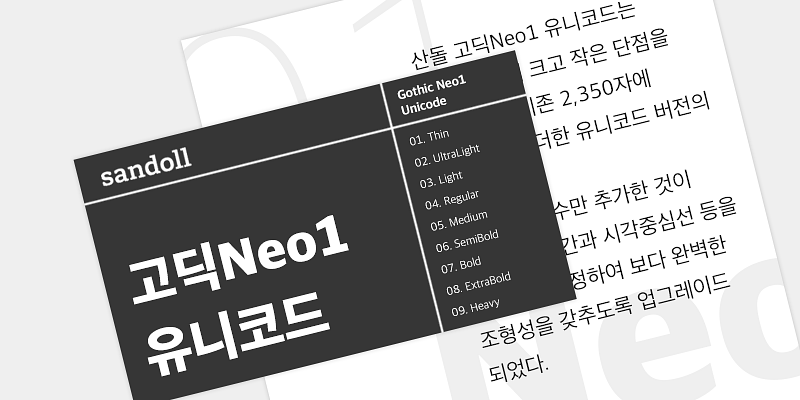
Sandoll GothicNeo1 est une police gothique haut de gamme avec une superfamille de différentes graisses.
Cette police, qui fait partie de la série Sandoll Neo, allie la technologie et la grande expérience de Sandoll dans la création de polices, en modernisant l’élément traditionnel de la Sandoll Gothic.
La police est optimisée pour le confort de l’utilisateur, et les lettres carrées de base ainsi que les espaces parfaitement alignés entre chaque lettre donnent à la police une apparence stable.
Sandoll (산돌) est une grande fonderie typographique basée en Corée. En 40 ans d’activité, elle a créé près de 600 polices de caractères et peut se targuer d’une forte expérience dans les projets multilingues, tels que le développement CJK et la mise en correspondance des polices coréennes avec d’autres polices scriptes.